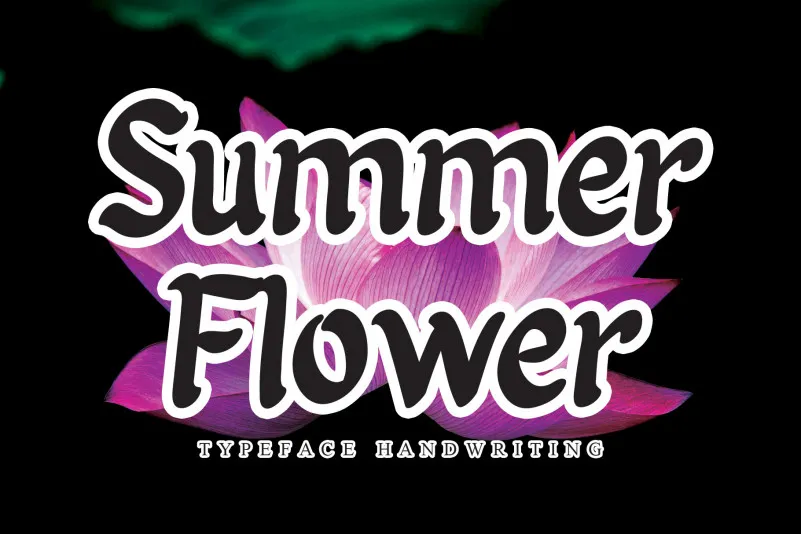
A Summer Flower Script Font é uma elegante tipografia script que destaca-se pela simplicidade e beleza. Perfeita para eventos festivos, essa fonte traz uma sensação aconchegante e envolvente à qualquer projeto gráfico. Suas linhas delicadas enriquecem as cartas de agradecimento, os convites de casamento, e mesmo as etiquetas da geladeira ou o logotipo da sua marca. Além disso, ela é ideal para criações empresariais como business cards, dando um toque singular a qualquer projeto que precise de uma pitada floral e delicada. A Summer Flower Script Font é perfeita para quem busca uma fonte elegante e versátil que se destaca em qualquer uso. Seja você designer ou criador de conteúdo, certamente vai apreciar o charme desta fonte do andikastudio.